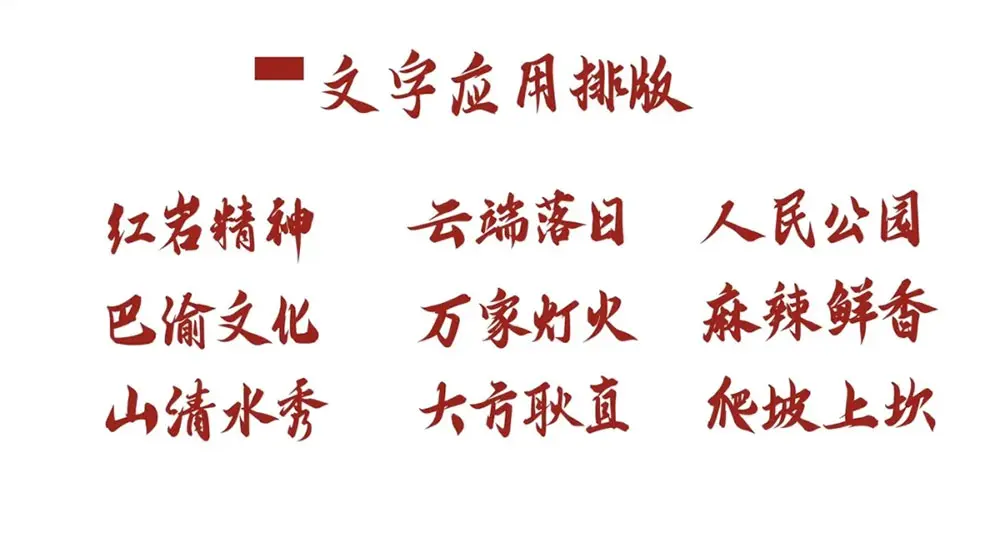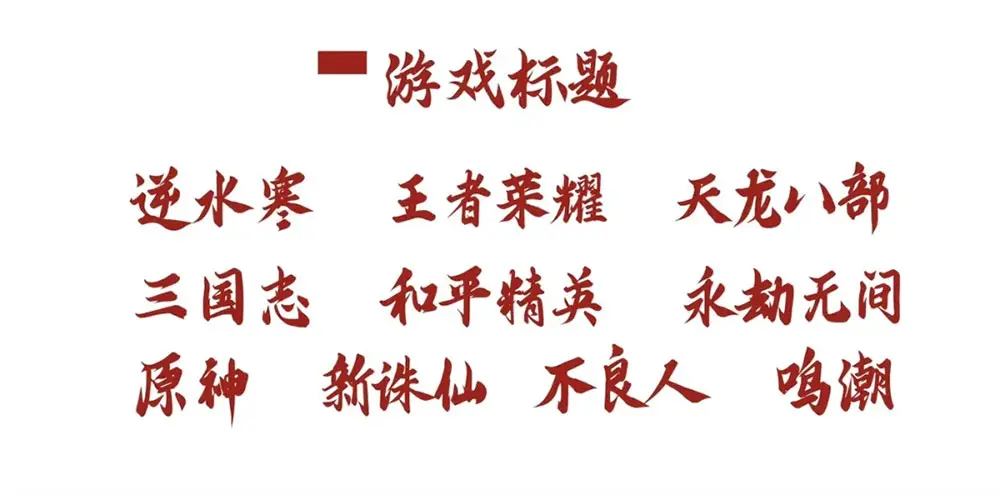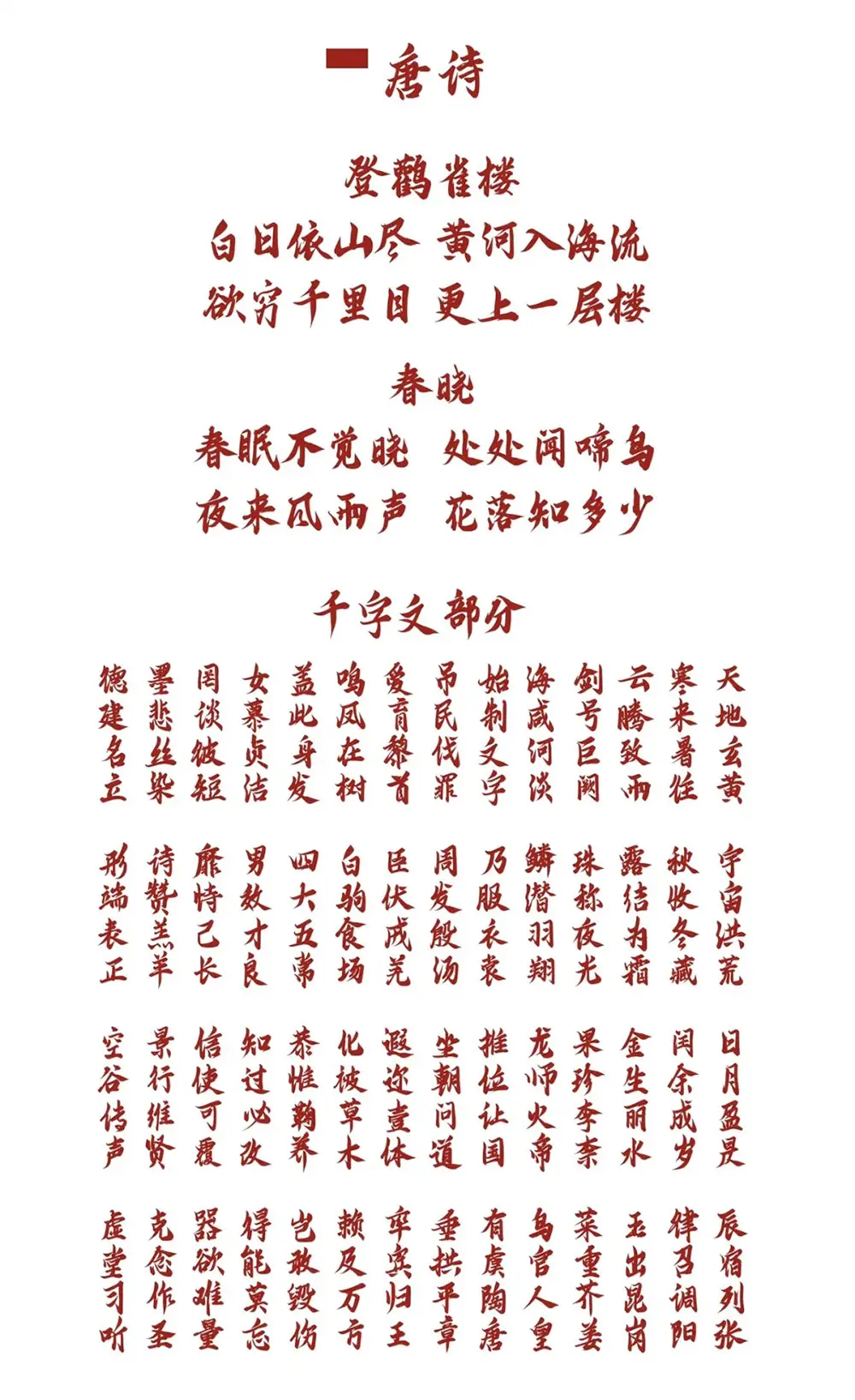
各位新老朋友大家好,很高興再次和大家見面,先自我介紹一下:雲峰字庫,一個來自重慶本土的字庫小品牌,一個人,一臺電腦,組成了它,因熱愛而存在,在此之前,已經發布了三款免費商用字體:雲峰飛雲體、雲峰靜龍行書、雲峰寒蟬體,承蒙厚愛,雲峰飛雲體得到了大家的認可,被運用於影視、包裝、平面、短視頻等渠道,感謝大家的認可。